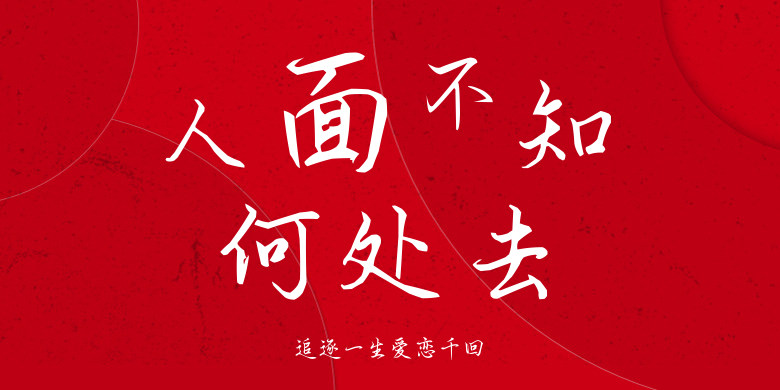
追逐一生爱恋千回
追逐一生爱恋千回,这款字体结构工整、笔画清晰,兼顾美观与易读性,适用于标题、正文、海报、包装、LOGO 等多种场景。字形优雅稳定,风格百搭耐看,适配日常排版与创意设计,让文字呈现更舒适、更具质感。追逐一生爱恋千回一笔一画,皆是细节,以均衡的比例、流畅的线条打造舒适视觉体验,字形端正大气,风格简约现代。无论是商业设计、品牌宣传还是日常排版,都能轻松驾驭,让文字更有格调与力量。追逐一生爱恋千回字体下载。